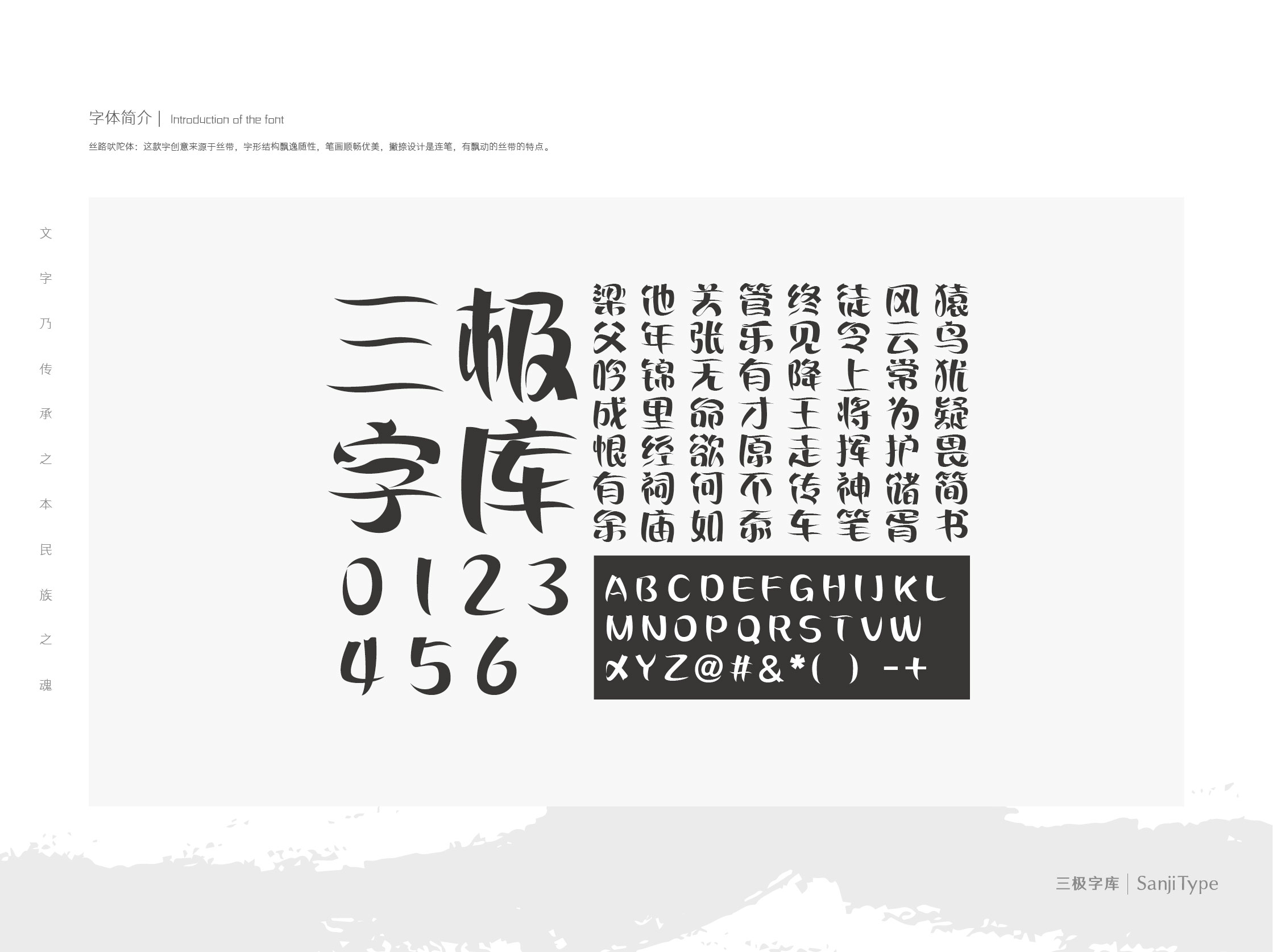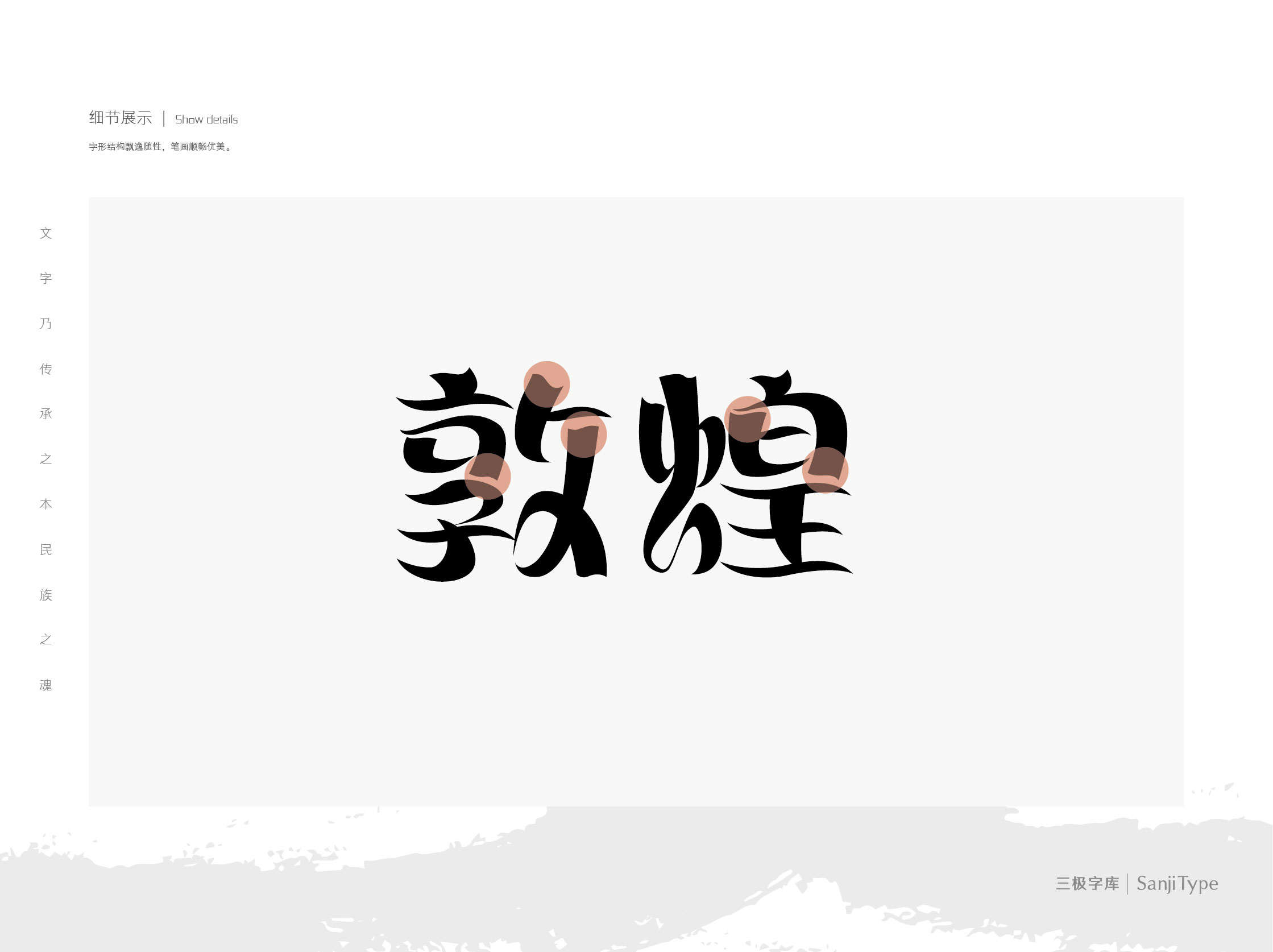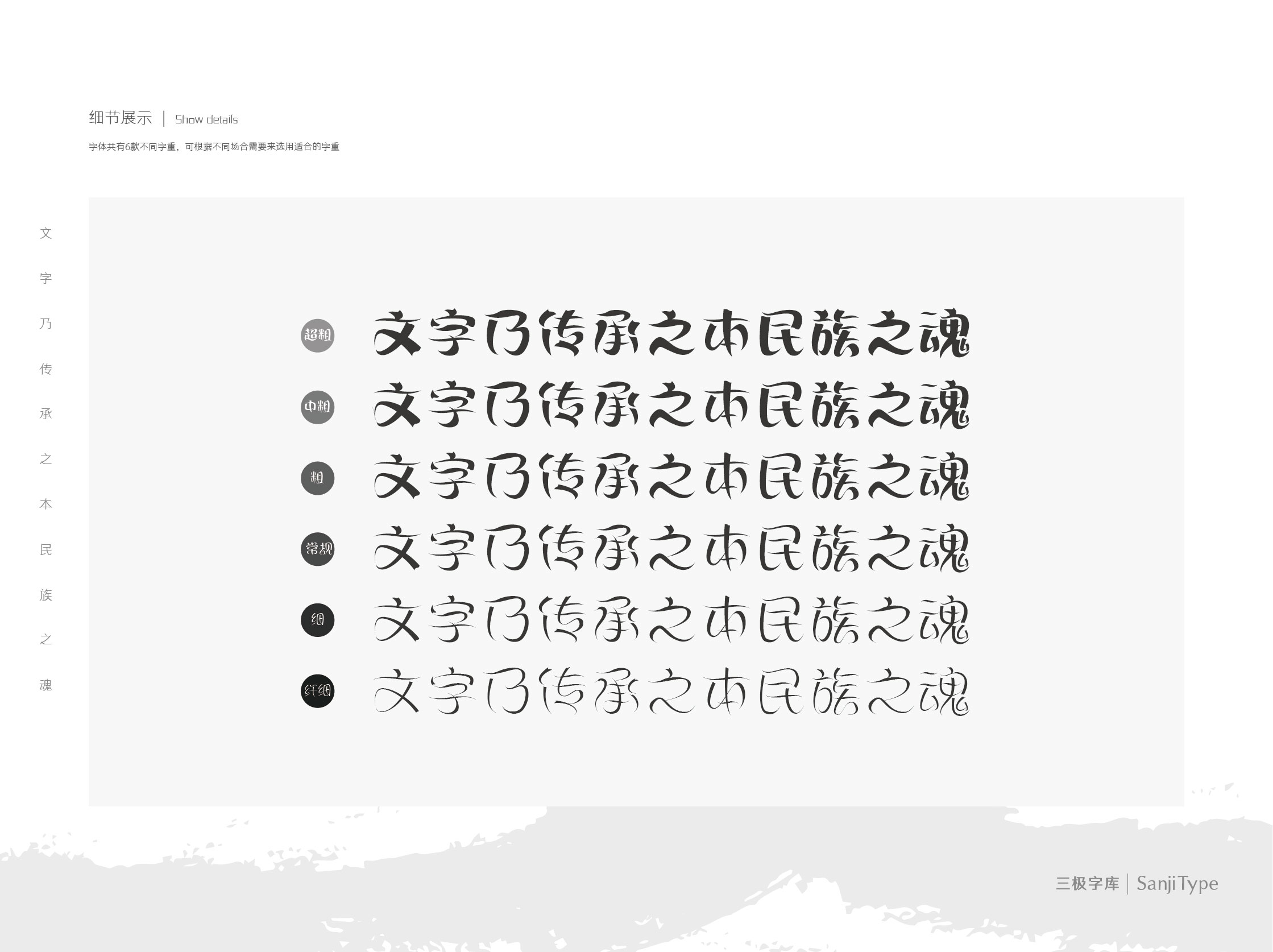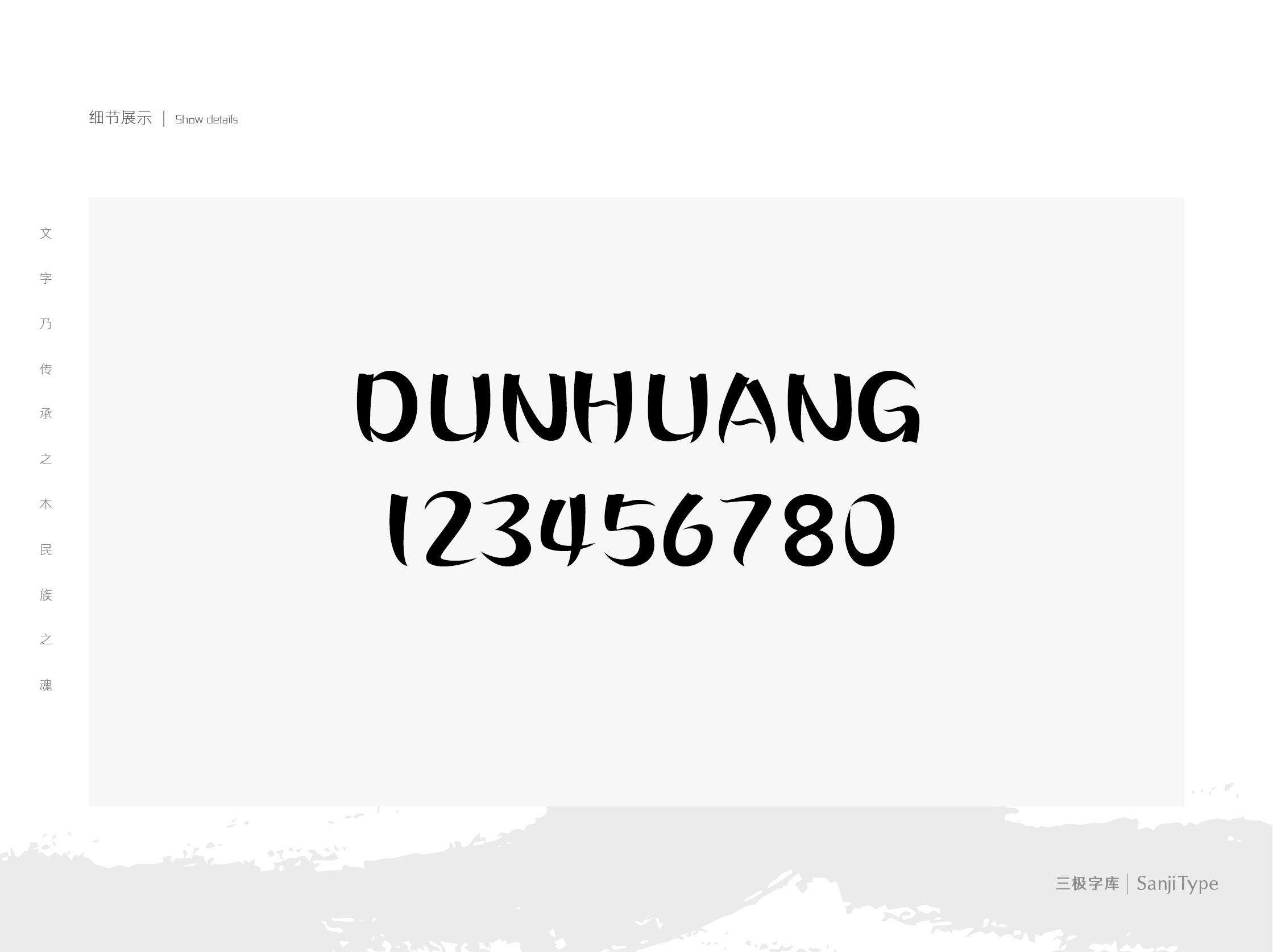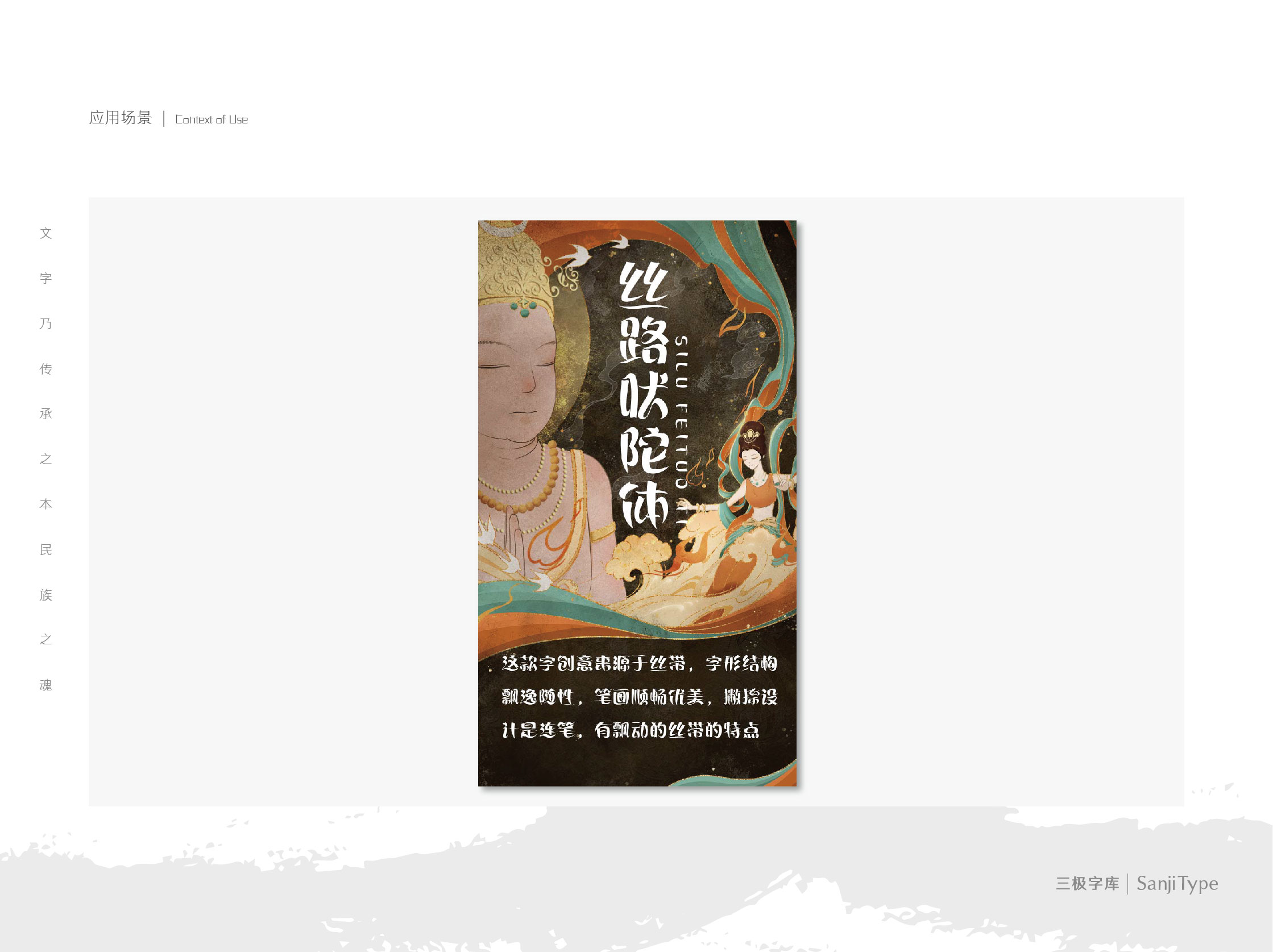
丝路吠陀体
显流动飘逸之美
字体简介
三极字库与敦煌博物馆合作推出带有浓厚敦煌色彩的美术字——丝路吠陀体。这款美术字体的底层创意来源于丝绸,笔画中间粗俩端偏细,富有弹性。转折弧度优美流畅,笔画间有自然连笔设计,饱含流动飘逸的绸缎之感。希望这款字体的研发、推广、运用,不仅为敦煌文化注入新活力,更为各界品牌增效赋能。